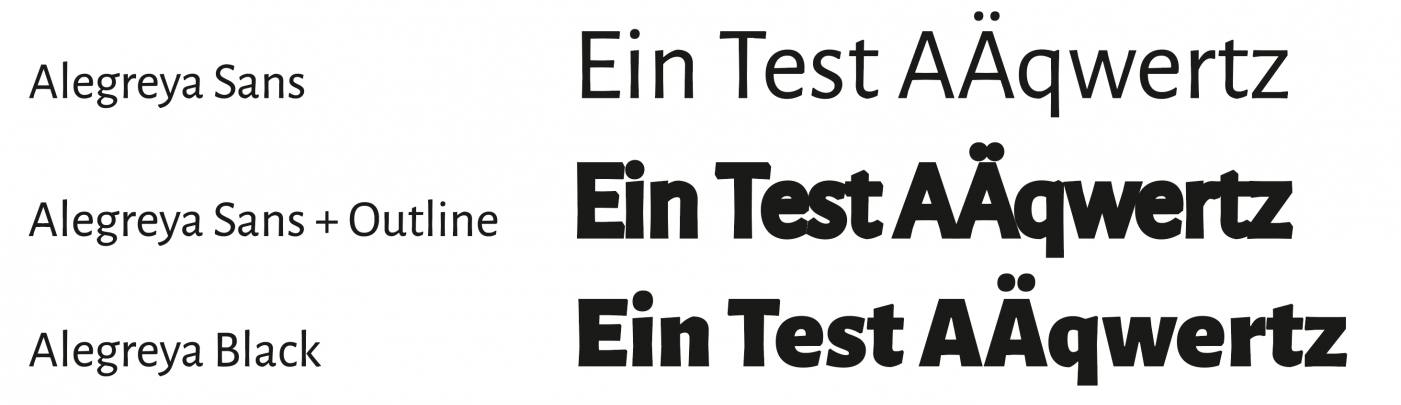
Kostenlose Schrift, die Geld kostet
ist es üblich, dass manche Fonts auf einigen Websites kosenlos angeboten werden und auf anderen kostenpflichtig sind? Als Beispiel:
Leider ist das auf einigen dubiosen Webseiten üblich. Legal ist es in den allermeisten Fällen nicht, aber die Verfolgung von Raubkopien ist teuer und aufwändig.
In deinem speziellen Fall »Glober« ist es dagegen so, dass bei dafontfree nur die beiden kostenfreien Schnitte zur Verfügung stehen, die auch bei FontFabric kostenfrei erhältlich sind. Es ist deswegen auch die "EULA Free Font License Ver. 2.0.pdf" von FontFabric enthalten.
Danke! Da fällt mir eine andere Frage ein: Wenn ich z. B. eine Font in Regular für umsonst bekomme, dann kann ich ja im Vektorprogramm einfach eine Kontur einfügen und so auf die Stärke einer dickeren (bold) kommen. Die Frage lautet: Gibt es optisch Unterschiede, wenn ich eine Kontur benutze oder eben die dickere Variante kaufe? Das frage ich mich sehr oft :-)
Oh ja, da gibt es sogar sehr große Unterschiede! Schau Dir nur mal die Punzen an: Im echten Schriftschnitt sind diese in ihrer Größe und Form exakt auf die übrigen Proportionen der Schrift abgestimmt. Legst Du hingegen eine Kontur um die Buchstaben, werden die Punzen überproportional kleiner, laufen im Extremfall sogar zu. Und auch die Außenformen der Zeichen werden verändert, kleine Formen und Zwischenräume laufen zu und die Gesamtformen der Zeichen werden mit wachsender Konturstärke zunehmend plump. Auch das Spacing wird durch die Kontur verändert, die eigentlich sorgfältig definierten Abstände zwischen den Buchstaben werden durch die Kontur verringert. Der Charakter des Fonts wird durch so eine Kontur in unterschiedlicher Weise zu seinem Nachteil verändert.
im Vektorprogramm einfach eine Kontur einfügen
Ein schneller Test zur Verdeutlichung:
Stimmt, das ist deutlich zu sehen. 🙄
Verpunzt und zugelaufen, das ist ja gar nix ...
Wie sähe das ganze "notverfettet" aus durch B klicken bei Fonts ohne Boldschnitt, falls das jemand für einen Test abschalten kann? Das wäre ja die "Alternative", siehe andere Diskussion ...
Und was deine Eingangsfrage anbelangt, Das gibt es trotzdem tatsächlich. eine kostenfreie und auch legal für jede Anwendung nutzbare Dafont-Version und eine kostenpflichtige z.B. über MyFonts.
Grund: Der Font wird erst einmal in einer durchaus schon einsetzbaren Version, mit z.B. nur dem Grundumfang an lateinischen Buchstaben, Zeichen und den gängigsten Satz- und Sonderzeichen, den wichtigsten Kening-Paaren und nur einem automatisch erstellten Kering, und oft eben einer recht zufälligen Lage der Knoten in den Buchsabenkonturen, die dann in großer Schriftgröße deutliche Knicke aufweisen.
MyFonts hat aber auch ein Auge auf Dafont-Neuerscheinungen, und dann bekommt man von denen ein Angebot, aus dieser Schrift nach deutlicher Überarbeitung eine professionelle Schrift zu machen, die dann über MyFonts vertrieben werden kann. Hier müssen dann die Konturen der Glyphen kräftig überarbeitet werden, die Schrift soll dann auch händisch gemachtes Hinting bekommen, und evenuell auch ein deutlich vergrößerten Zeichenumfang, auch ist es Möglich, dass die Schriftart dann sogar zu einer ganzen Font-Familie mit unterschiedlichem, aber eben nicht nur durch einfaches Interpolieren erzeugte Versionen mit unterschiedlichen Gewichten und Weiten, oder auch echter Kursiver ausgebaut werden.
Ich hatte auch einmal so ein Angebot. Es war eine Schriftart, die zu Bleisatzzeichen aus jewweils einer geingen Zahl oberer Glyphenhälften und einer ebenso kleinen Anzahl aus unteren Glyphenhälften kombiniert wurden. Ich bin zunächst auch auf dieses Angebot eingegangen, bis man von mir verlangte, dieses Konzept, dass die Glyphen aus einem möglichst minimalen Sortiment aus Glyphen-Hälften kombiniert wurden aufzugeben, und unter Beibehaltung der mittleren Trennlinie dann jede Glyphe jeweils für sich zu optimieren, Also dasses dann für jede Glyphe ein genau optimiertes Hälften-Paar gezeichnet werden sollte. Dies hätte aner dann das vom ursprünglichen Autor der Bleilettern erdachte Baukasten-Prinzip. Da ich ebenn nicht auf diese so zwangsläufig entstehenden ungeauen Übergänge zwischen oberer und unterer Hälfte nicht verzichten wollte, war dies ja gerade die Seele dieser Schrift, habe ich dann diese Zusammenarbeit aufgegeben.
Das war bei mir damals die Border Control: http://www.peter-wiegel.de/BorderControl.html
Und so gibt es eben manchmal eine nicht ganz so optimale Freeversion, und eine optimierte Pro-Version einer Schrift, durchaus vom gleichen Autor, und beides dann auch Legal-
Bitte verstehe das nicht falsch, es gibt natürlich auch viele illegale Font-Download-Seiten, die kein Problem damit haben, kostenpflichtige Schriftarten einfach als frei und kostenlos nutzbar zu vertreiben. Dafont ist aber gut moderiiert, das bedeutet, der Bereiber prüft auch jedenn eingelieferten Font vor der Veröffentlichung, und reagiert auch auf Meldungen bei dann durchgerutschen illegalen Fonts, dass man hier frei erhältliche Fonts recht sicher auch einsetzen kann, reicht einem für das Vorhaben dann auch die Qualität der dort angebotenen Schriften. Will man die Schrift im professionellen Umfels intensiv nutzen, lohnt sich aber dann doch der Kauf der Pro-Lizenz.
Vielen Dank für die ausführliche Antwort. Das klingt so, als ob Schriften bei myfont.com geprüft werden und eine Art Qualitätsstandard vorhanden ist?
Ja, beide Anbieter, die Du nanntest, haben ihre Qualitätsstandards, wobei die bei Schriftarten, die auch von unerfahrenen Hobby-Designern erstellt wurden, diese natürlich deutlich geringer sind, schließlich ist hier das übliche Ausgabegerät ein normaler Heimdrucker, der eben auch leicht mit sehr unsauberen Konturen klar kommt.
Beim Anbieter professioneller Schriften müssenn die aber auf allen möglichen Ausgabegeräten funktionieren, also auch Schneidplotter, die natürlich Buchstabenkonturen mit sich teilweise überschneidende und vielen Richtungswechseln Vektoren natürlicgh überhaupt nicht gebrauchen können.